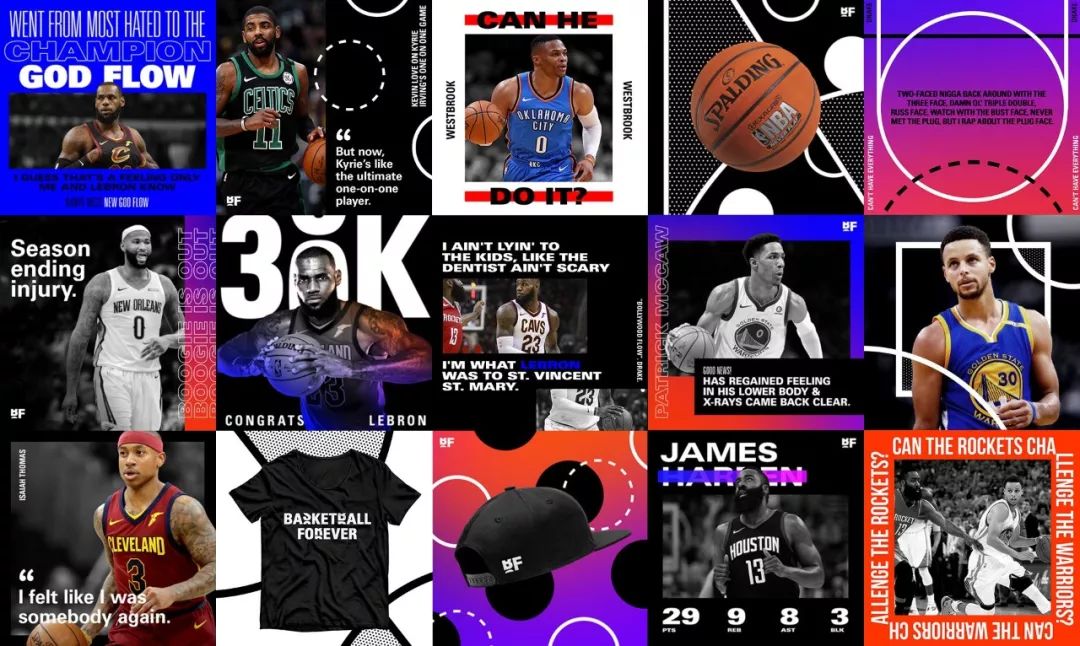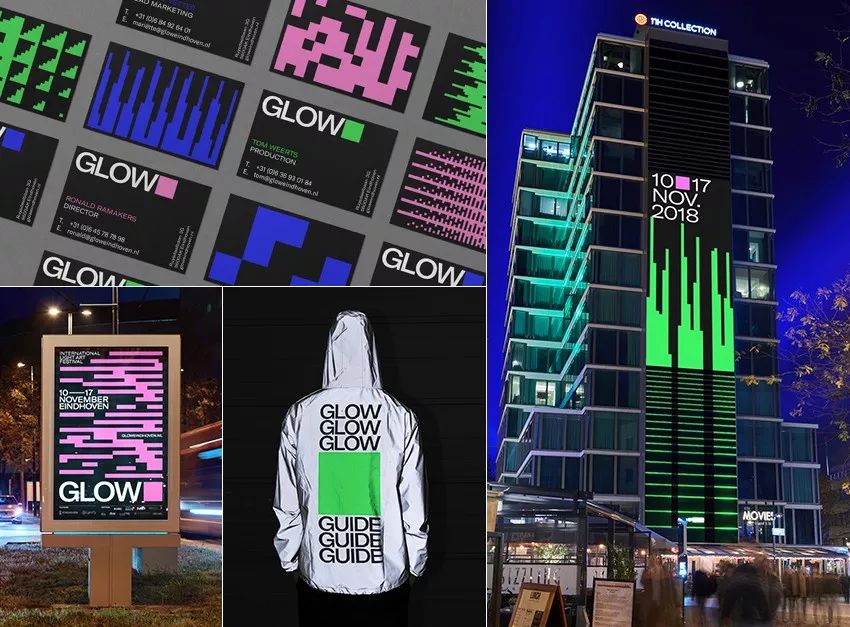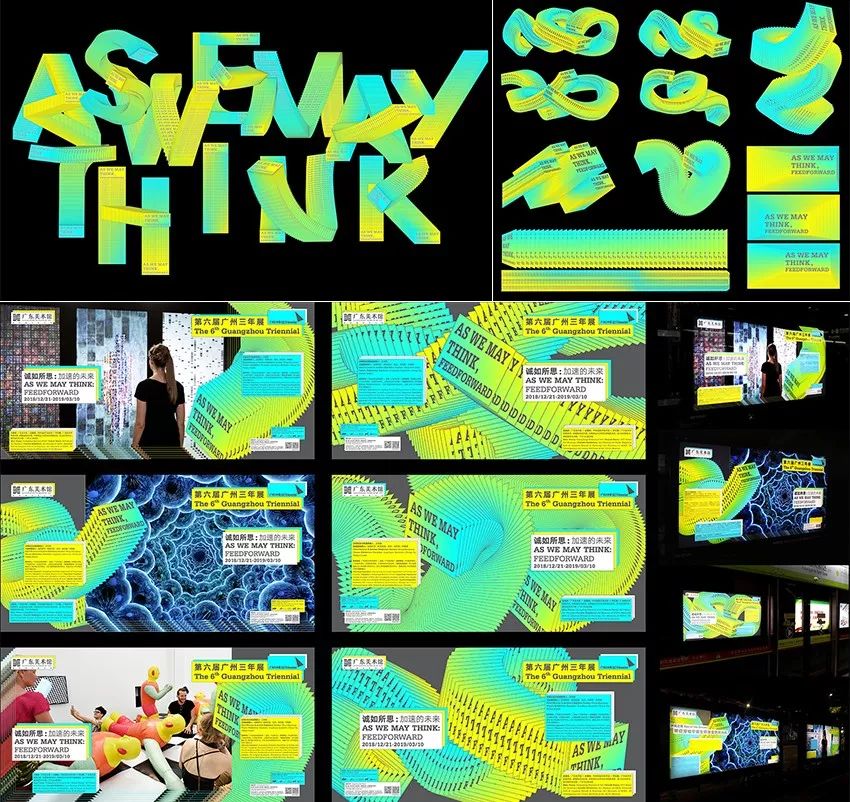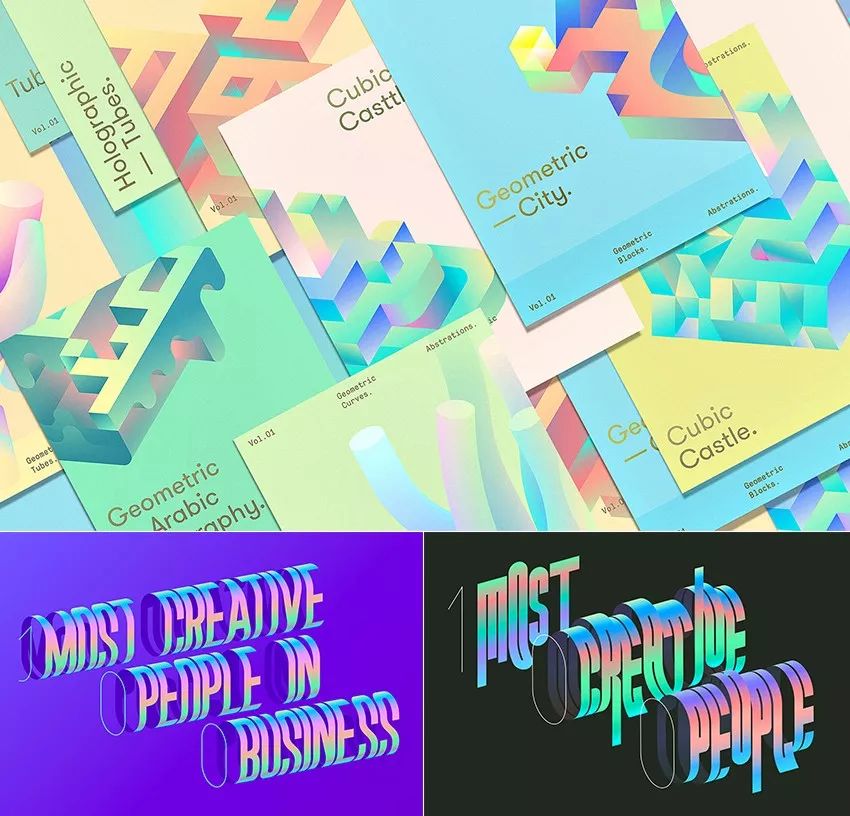
12个你不得不知的平面设计趋势
为和大家分享关于设计趋势的见解,ISUX研究了2019-2020的设计趋势。没有必要去遵循年度设计趋势报告,但是否意识到这一趋势,对设计师而言却非常重要。首先我们总结了平面设计的总体趋势,然后是最近延展出来的IP形象,同时也对从Zepeto app 和 Memoji开始的,最近扩展出来的角色设计趋势有所研究,最后则是UX趋势的分析。
ISUX has done a design trend research to share insights on 2019 - 2020 design trends. It is not necessary to follow the annual design trend report, but it is important whether the designer is aware of the trend.First, we summarized the overall graphic designtrends and then went through the recent expansion of the character market.Also, we have researched the avatar design trends started from the Zepeto appand Memoji and analyzed the UX trend for the last.
本文想分享ISUX设计趋势报告的第一部分“图形设计趋势”。这部分展示了当下各种品牌和动态图形的案例,总结了12个值得注意的平面设计趋势。
In this article, we would like to share ‘General Design Trends’, the first part of the ISUX design trend report. ‘General Design Trends’ shows recent branding and motion graphic cases and summarizes 12 notable trends in graphic design.
排版一直是设计的重要元素,也是传达品牌强烈信息的手段。从去年开始,粗大的无衬线字体和强有力的排版被应用到许多品牌设计当中,这使得它成为平面设计趋势的一部分。此外,也有越来越多的品牌采用动态和反映了3D趋势的三维字体版式设计。
Typography is constantly an important element in design and is used as a method of delivering strong brand messages. Since last year, a lot of brands applied bold San-serif fonts or used strong typography on their designs which has made this become a part of graphic design trend. In addition, there are a lot of typography cases that applying motions and can also find cases applying three-dimensional effect to typography reflecting 3D trends.
动态字体海报
这张动态排版海报不是简单地放置图形和文字,而是将移动的3D文字放在固定的图形上,传达新的视觉印象。这些图形主要通过SNS以短循环视频的形式共享。
This is a moving poster design with a kinetic typography concept. Beyond simply placing image and text, three dimensionally moving text over a fixed image conveys a new impression. These graphics are mainly shared through SNS in forms of short looping video.
Uber品牌识别
Uber开发了一种无衬线字体用于品牌logo的再设计,并将其贯穿于整个品牌系统。采用了这些品牌字体的动态海报,更为有力地传达出Uber的品牌信息。
Uber developed San-Serif brand fonts along with logo redesign and applied them throughout the brand system. Uber's moving posters designed with their brand font delivers Uber’s brand messages more strongly.
Squarespace品牌识别
Dia studio常将动态文字应⽤于品牌项⽬,“Squarespace”是其代表作品之一。
Dia studio often applies kinetic typography to their branding projects. This ’Squarespace’ branding is one of their representative portfolio.
FAD视觉图形
以3D形态传递活动信息的版面设计,就像礼品包装一样。这种循环的gif图也作为品牌主图形被运用。
A typography made with design event information applied in 3D form as if it were a gift wrapping. A looping gif image was applied as a main graphic.
韩国耐克女性运动广告
韩国艺人支持女性主观活动的耐克运动广告,也采用了大胆的哥特式字体。这些由Guteform设计工作室设计的字体有基本的延展形式,同时有一个系统能延展成更为宽大的形式以适配媒体的比例。这种动态化的强烈的排版传递了活动信息,和其他设计元素的互动,最大限度地发挥了图形效果。
The Nike Women's advertising campaign in which Korean celebrities appear to support the subjective life of women, also applied bold gothic for their font. This font, designed by Design Studio Guteform basically has an extended form and also has a system that extends to a wider format to match with the proportion of the media. Dynamic and intense typography delivers messages of the campaign and interacts with other design elements which maximizes the graphic effect.。
随着Instagram用彩色渐变作为品牌色,渐变趋势已经持续好几年。最近品牌、UI和包装的图形设计都采用明亮而强烈的对比色,这种趋势不仅应用于设计,也应用于摄影。强烈的色彩组合,梦幻的色调和彩色渐变有望应用于2019年的整体设计。
As Instagram applied colorful gradient for their brand color, color gradient trends have been going on for several years. Recently, bright and strong contrasted colors have been used in all graphics of branding, UI, and package design and this trend is applied not only to graphics but also to photography. The strong color combination, dreamy color tone and colorful gradient are expected to be applied to overall design in 2019-2020.
APP图标设计
越来越多的手机APP图标使用渐变色。
Recently a lot of mobile apps apply colorful gradients on their icon design.
欧洲体育—2018平昌冬奥会品牌识别
欧洲体育台2018年平昌冬奥会的转播也将强对比和渐变色运用于多数场景中,包括logo,图形和摄影。荧光图形和深⾊背景的对比,尤为深刻地凸显了冬季运动的感觉。
Eurosport's 2018 PyeongChang Olympic broadcast also applied strong color gradient to all the application designs including logos, graphics and photography. Especially, the contrast of fluorescent graphic and the dark background emphasis the feeling of winter sports.
Basketball Forever品牌识别
NBA品牌重塑项目所使用的,诸如彩色渐变和大胆排版的设计方法,也反映了最新的趋势。他们创作了一个系统,通过各种颜色,字体和布局的应用,可以产生各种图形输出。
This is a rebranding project of NBA news broadcasting company which reflects the latest trends like using colorful gradients and bold typography. They applied a system which various graphic outputs can come out by applying various colors, fonts and layouts.
明日之子品牌识别
腾讯视频和哇唧唧哇联合出品的选秀节目明日之子,用多种渐变色圆形表达不同选手的才华。随着节目的进行,图形主题也会随选手的变化而变化。
A branding for Tencent Video and Wajijiwa’s idol audition program ‘Mingri Zhi Zi’, expressing the talents of the participants with colorful gradients in different forms of circles. Graphic motifs changes with participants as the program goes on.
A trend does not flow in one direction but can extend to various ways as we see how latest design trend reflects technologies such as 3D and AR/VR but also contains the retro style. I hope that these various design trends will be applied in a new way, so that new and interesting designs can be created.